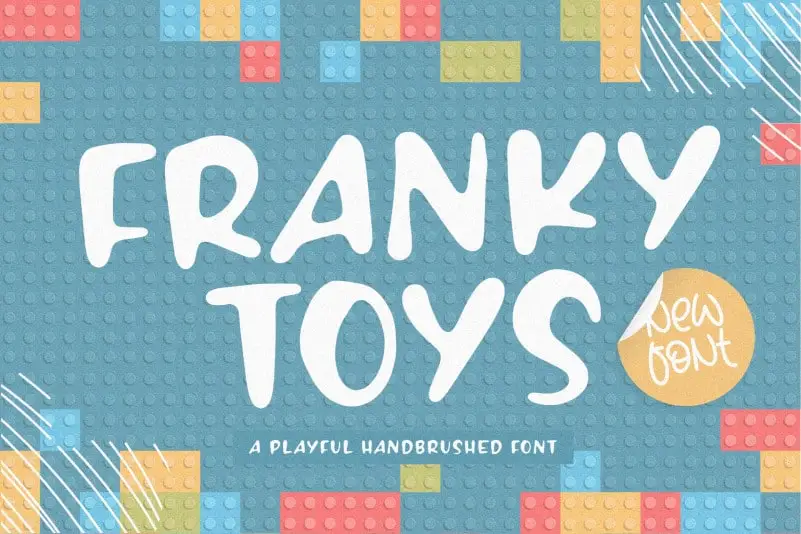
FRANKY TOYS Playful Handbrushed Font – Download Grátis
A fonte ‘FRANKY TOYS Playful Handbrushed Font’ é perfeitamente adequada para uma ampla gama de projetos de design. Com seu estilo delicado e desenhado com um pincel, essa fonte traz uma sensação de vivacidade para qualquer projeto que precise de personalização. Seja em embalagens de produto ou criação de marca, a ‘FRANKY TOYS Playful Handbrushed Font’ pode destacar sua identidade visual de maneira criativa e elegante. Suas características suaves e detalhes cuidadosamente criados tornam-a perfeita para aplicações em revistas, redes sociais, eventos de casamento ou qualquer outra iniciativa que busque expressividade na superfície da página. Sua simplicidade permite a você explorar infinitamente as possibilidades do seu design sem comprometer a qualidade e beleza exclusiva deste recurso gráfico.